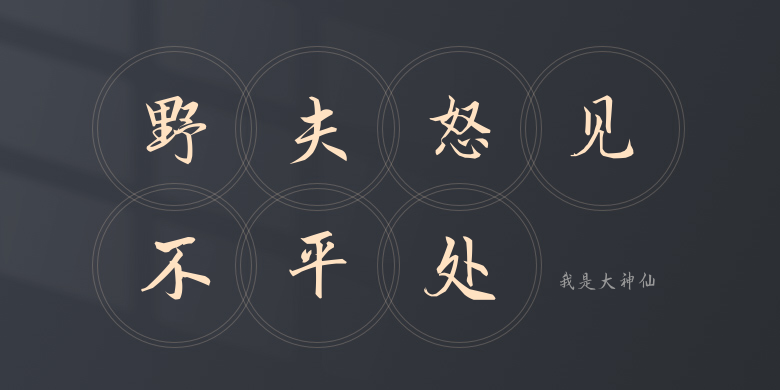
我是大神仙
我是大神仙,这款字体结构工整、笔画清晰,兼顾美观与易读性,适用于标题、正文、海报、包装、LOGO 等多种场景。字形优雅稳定,风格百搭耐看,适配日常排版与创意设计,让文字呈现更舒适、更具质感。我是大神仙一笔一画,皆是细节,以均衡的比例、流畅的线条打造舒适视觉体验,字形端正大气,风格简约现代。无论是商业设计、品牌宣传还是日常排版,都能轻松驾驭,让文字更有格调与力量。我是大神仙字体下载。